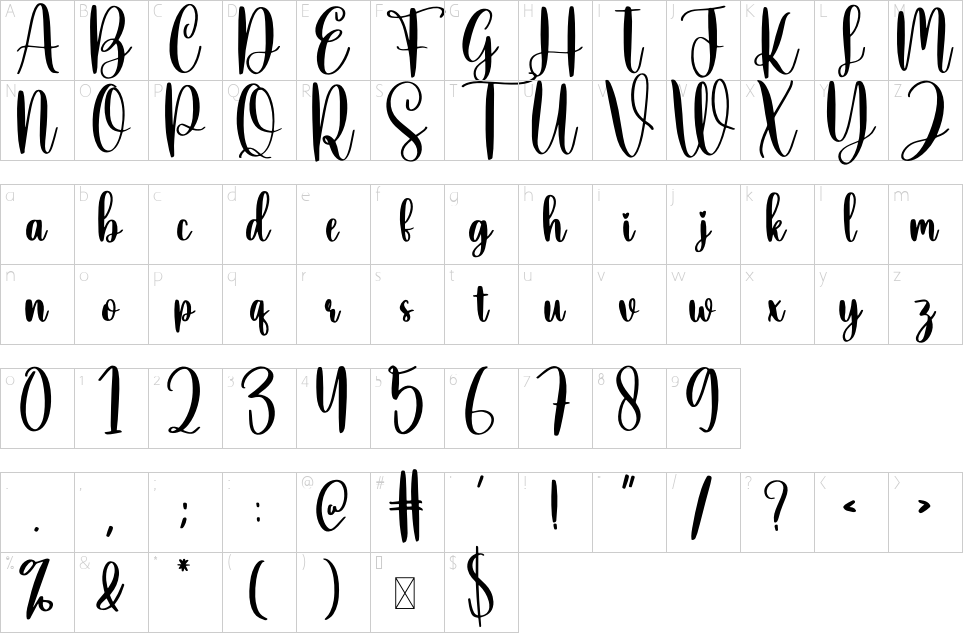
Earth Font é uma elegante e minimalista fonte gráfica que representa perfeitamente a essência do nosso planeta. Inspirada em desenhos naturais e formas geométricas, esta fonte foi criada pelo designer anônimo chamado scratchones e já foi baixada pelo número impressionante de 409 vezes. Perfeita para designers e profissionais que buscam uma fonte que transmita a força e vitalidade da Terra em seus projetos digitais, a Earth Font é uma escolha perfeita para aqueles que valorizam a simplicidade e a conexão com a natureza. Instale-a no seu computador hoje e deixe sua marca em qualquer design.